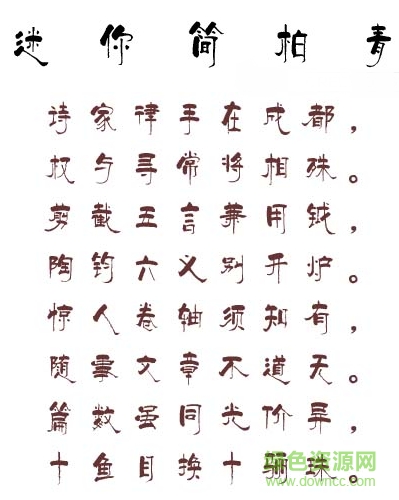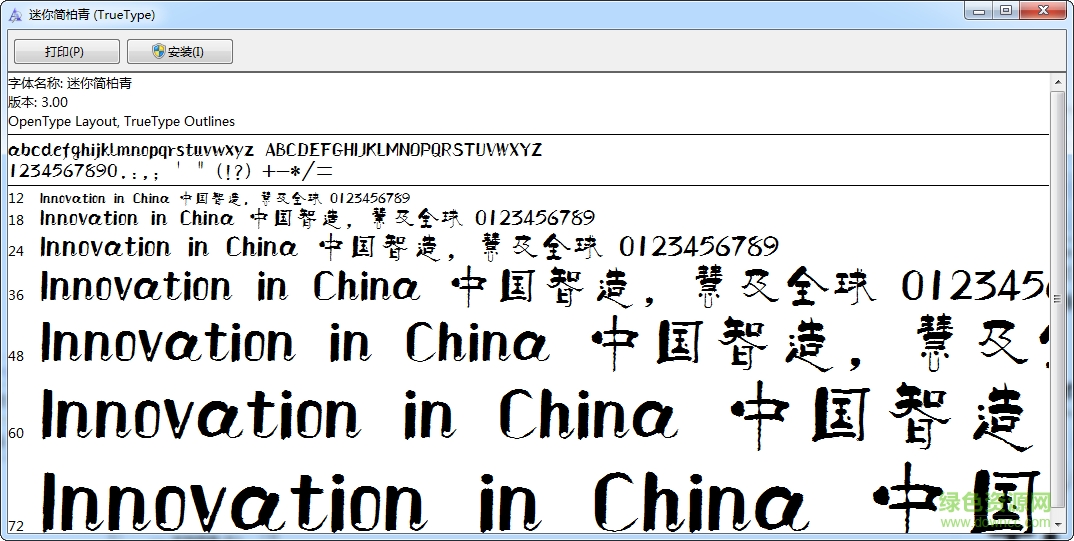
迷你簡柏青ttf是一款非常好用的迷你字體,支持中文簡體、英文以及阿拉伯?dāng)?shù)字,字體整體細(xì)長,非常的優(yōu)雅大方,歡迎喜愛此字體的用戶到綠色資源網(wǎng)下載使用!
該字體字體結(jié)構(gòu)端正、重心平穩(wěn)、美觀實(shí)用、清晰醒目。適合應(yīng)用于廣告設(shè)計(jì)、名片設(shè)計(jì)、包裝印刷、產(chǎn)品設(shè)計(jì)等應(yīng)用。歡迎來綠色資源網(wǎng)下載。